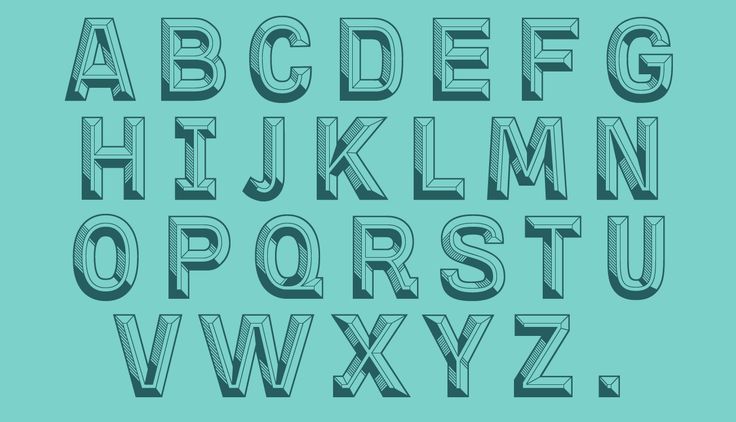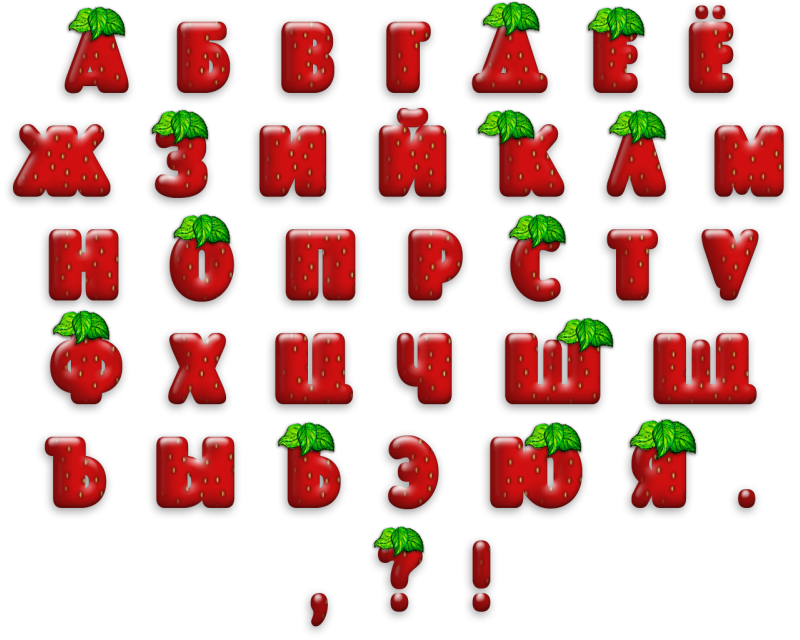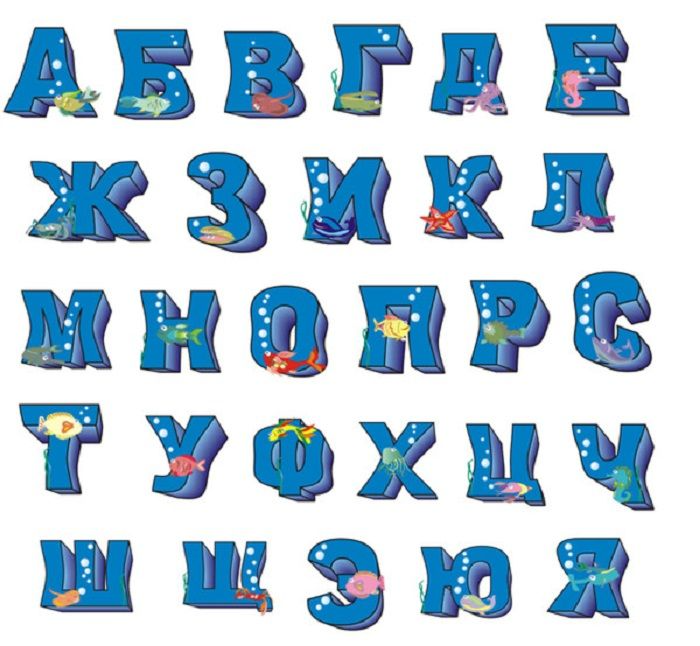
Объемный русский шрифт: 3D шрифты (548 шрифтов скачать) 🌴 FontsIsland.com
Зачастую при текстовом оформлении документов (будь то реферат, доклад или, возможно, презентация) мы сталкиваемся с дефицитом красивых русских кириллических шрифтов. Красивые шрифты на русском языке довольно трудно найти в интернете, как правило, все, что предлагает нам сеть – это шрифты, которые ориентированы на иностранные тексты (в основном, это гарнитуры, разработанные для англоязычных пользователей). Предлагаем Вашему вниманию 10 наиболее интересных вариантов русских шрифтов. Среди предложенных гарнитур можно отметить разные стили, соединения, варьирующуюся толщину штрихов, меняющуюся контрастность, а также толщину засечек. Подобранные виды шрифтов достаточно резко отличаются друг от друга, благодаря чему появляется возможность выбрать среди них тот, который подходит для оформления сайта или вывески наилучшим образом.
Итак, давайте рассмотрим несколько красивых кириллических шрифтов:
- Tangak – красивый русский кириллический шрифт.
Данный вариант надписей очень эффектно смотрится на вывесках, при одном взгляде на него вспоминаются тонкие восточные мотивы. Тексты, напечатанные шрифтом tangak, изображаются с помощью техники несвязных соединений – это надпись, в которой буквы не соединены между собой. Шрифт достаточно гармонично будет смотреться, если использовать его для оформления названия кафе или ресторана.
- Ксеркс винди – инересный русскоязычный шрифт
Зачастую за красоту надписи приходится платить, шрифт ксеркс винди – яркий тому пример. Для того, чтобы прочесть изображение, написанное с помощью данного русского кириллического шрифта, необходимо приложить некоторые усилия. Несмотря на этот факт, будет справедливым отметить, что оригинальные резкие штрихи, с помощью которых изображаются буквы в данном наборе гарнитур, идеально подойдут для оформления веб-страницы или даже целого сайта.
- Porsce – стильный русский шрифт
Названный в честь известной марки автомобиля шрифт Porsche, несмотря на свое американское происхождение, ориентирован на русскоязычные тексты.
С помощью таких равномерных линий можно смело оформлять титульные листы или целые презентации. В данном варианте исключены лишние декоративные элементы, что позволяет охарактеризовать изображения, выполненные с помощью этого шрифта, аккуратными или даже лаконичными.
- Astra – изящный русский шрифт
Этот красивый русский шрифт, несомненно, идеально подойдет для того, чтобы изысканно оформить поздравительную открытку или, к примеру, обложку литературного произведения. Главной отличительной особенностью этого шрифта становятся утолщающиеся книзу части каждой из букв, а также «вздернутые» засечки. Тонкость и изящество – основные преимущества русского шрифта
- Ds down cyr – оригинальный русскоязычный шрифт
Объемный красивый русский шрифт ds down cyr будет довольно интересно смотреться при оформлении рекламных баннеров, но не стоит забывать о том, что такого рода надписи, помимо привлечения внимания, имеют и некоторые недостатки.
Так, текст, выполненный с помощью данного вида шрифта, будет достаточно трудно расшифровать, это обусловлено отсутствием пробелов внутри букв. Однако существуют ситуации, в которых читабельность текста стоит далеко после броскости и оригинальности.
- Bonzai – утонченный кириллический шрифт
Несмотря на то, что такого рода буквы ориентированы на русскоязычные тексты, шрифт bonzai, благодаря своим игривым тонким штрихам в сочетании с толстыми линиями, навевает атмосферу востока. Применение такому виду гарнитур можно найти на свое усмотрение, но универсальным этот русский шрифт назвать нельзя.
- Sevilla Décor – выразительный русский шрифт
Завитые засечки букв этого красивого русского шрифта гармонично будут смотреться в заголовке сайта или на страницах литературного произведения. Основным достоинством шрифта sevilla décor является то, что в процессе написания текста с помощью этой гарнитуры можно сэкономить пространство – изящные тонкие линии вполне этому способствуют.
- Dollar — массивный русский кириллический шрифт
Этот шрифт вполне можно использовать для оформления отчетов по работе, таблиц и графиков. Мощные толстые линии в сочетании с небольшим расстоянием между буквами «внушают доверие» и выглядят довольно солидно. Несмотря на свою строгость, русский шрифт
- Rostov – гротескный русский шрифт
Названный в честь города Ростова-на-Дону красивый шрифт Rostov не оставляет шансов прочим представителям гарнитур в подобном стиле. Четкие и понятные буквы будут актуальны практически в любой сфере.
- Uni Neue Light – современный русский шрифт
Этот вариант русского кириллического шрифта – несомненно, дань классике. Uni neue light можно использовать в рекламном ролике или информационном видео, так как тонкие линии и отсутствие засечек не будут привлекать к себе много внимания.
Надписи, выполненные с помощью этого шрифта, возьмут на себя единственно важную обязанность – проинформировать.
21 шрифт для презентации: выбор Canva